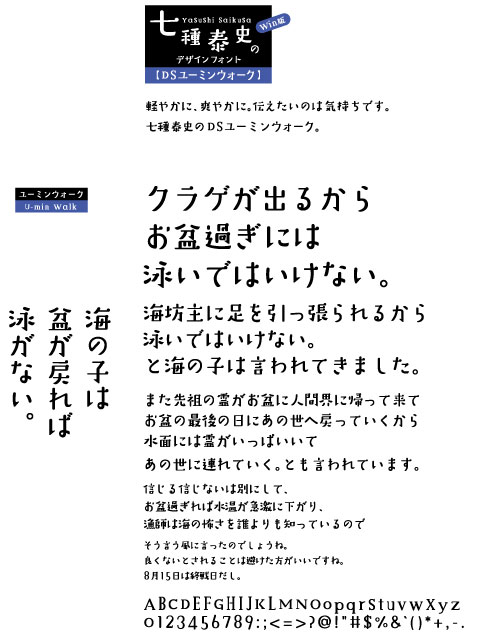
DSユーミンウォーク (DS-Uminwalk)
のほほんとした雰囲気が緊張感を和らげ、やさしい表情を醸し出すウォークシリーズ。
七種泰史/デザインシグナルの紹介
こころのこもった文字創りを目指す七種泰史氏のオリジナルブランド「デザインシグナル」。2008年夏からスタートし、年に2~3書体のペースで開発を進行中。多くのファンが新作を心待ちにする人気のブランド。